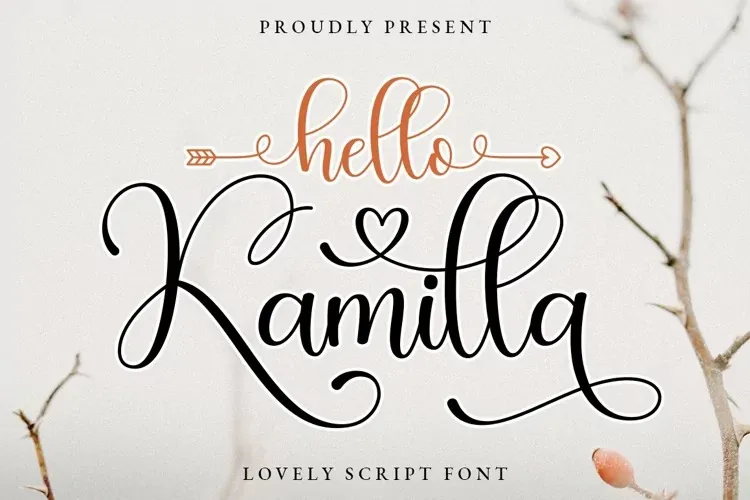
Este Hello Kamilla Font é uma tipografia romântica e encantadora criada pela Typesthetic Studio com swashes de coração e ligaturas. Perfeito para logotipos, estaçãorios de casamento, cartas, designs de presentes, fotografia, marcas de água digital, embalagens de produto e citações escritas a mão. O Hello Kamilla inclui um conjunto completo de alternativas maiúsculas, 2 swashes de minúsculas conectadas ao coração, 2 swashes de minúscula no início/no fim e mais duas para as minúsculas com ascender e descender. Além disso, o font vem com uma completa seleção de letras maiusculas e minusculas, símbolos multilíngues, numerais e pontuação, incluindo ligaturas. Este Hello Kamilla é ideal para quem está buscando um estilo agradável e criativo que se adapta a muitos usos na sua produção gráfica.